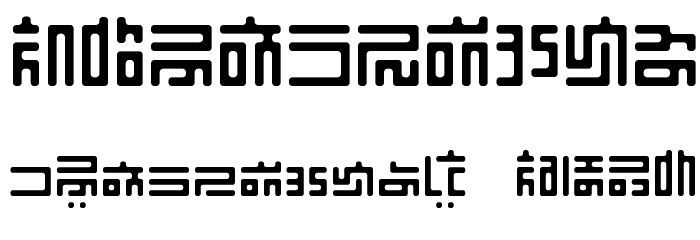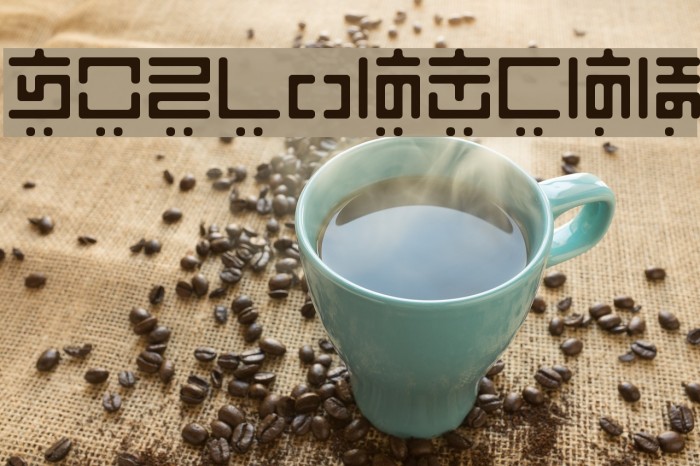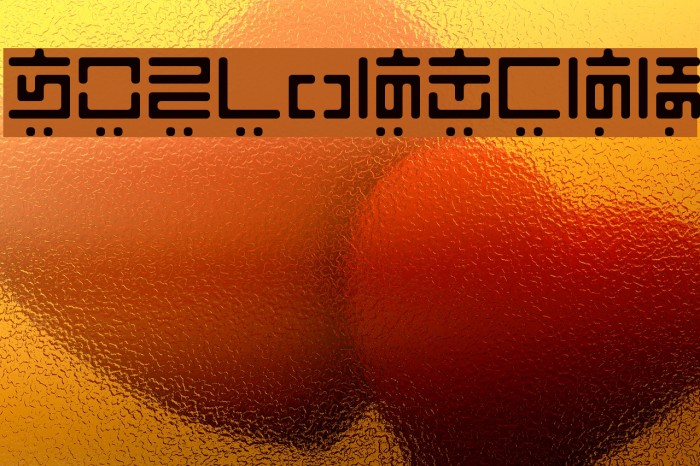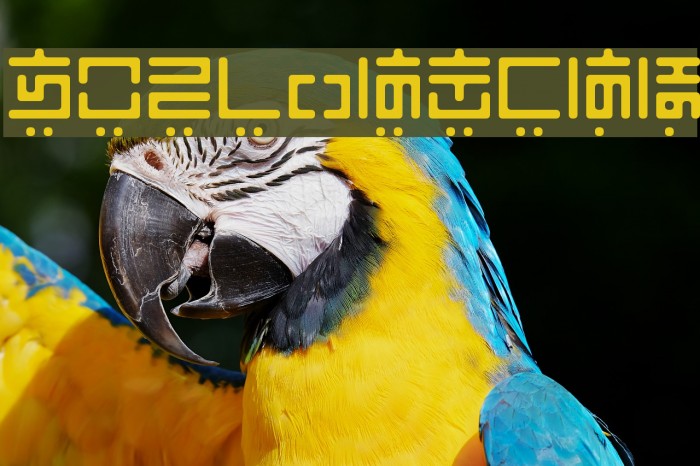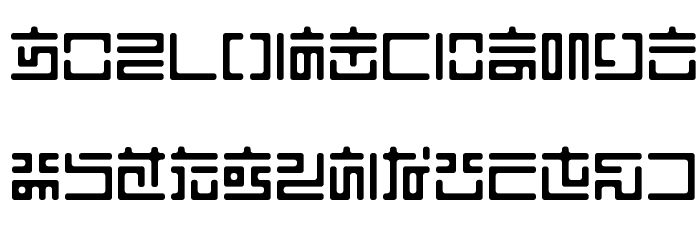
iiyodomu Font
| Anwendungsfall | Logos, Posters, Artistic Designs |
| Vorgeschlagene Projekte | This font is perfect for use in digital art, futuristic designs, sci-fi themed projects, and unique branding materials. |